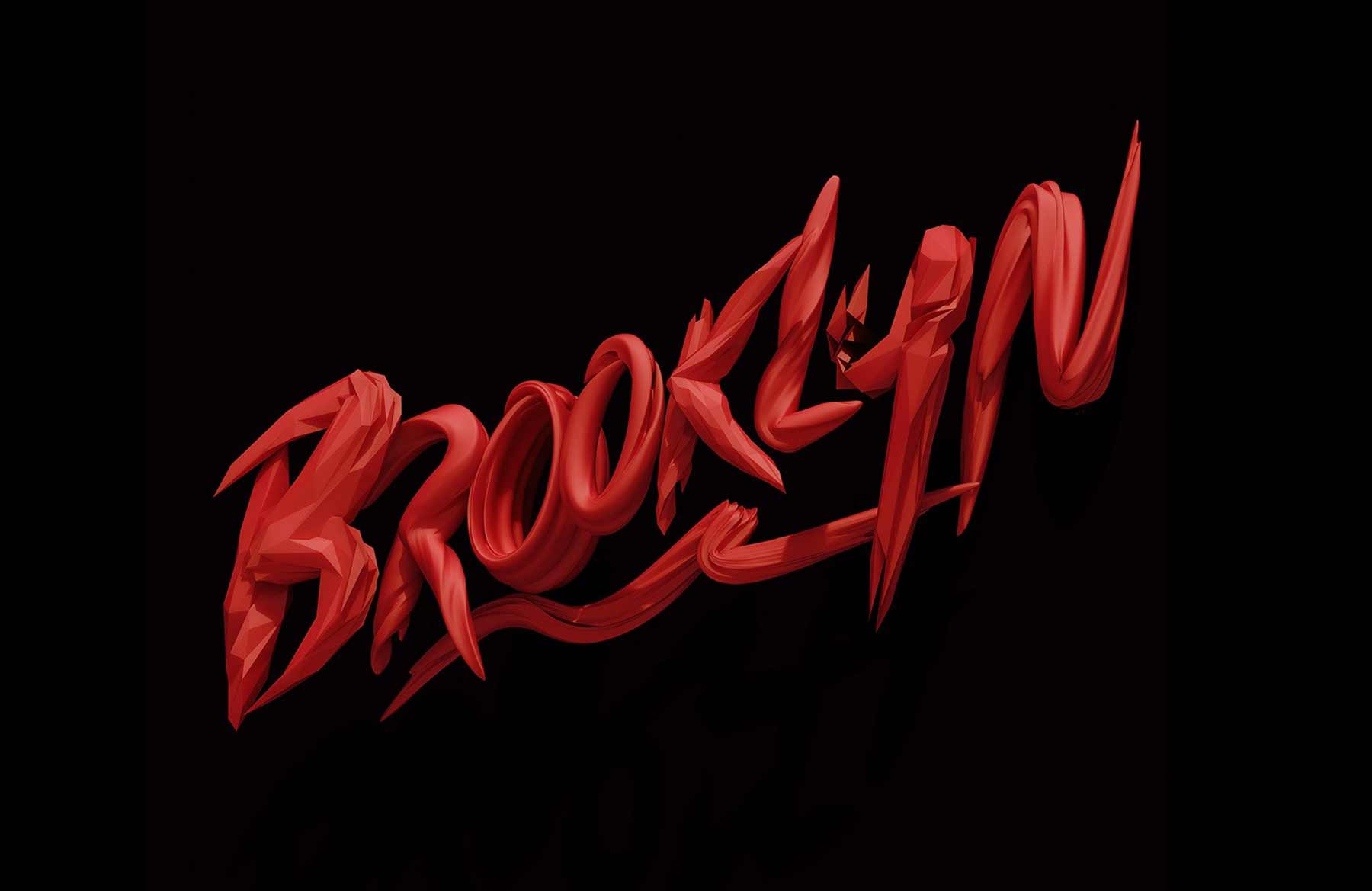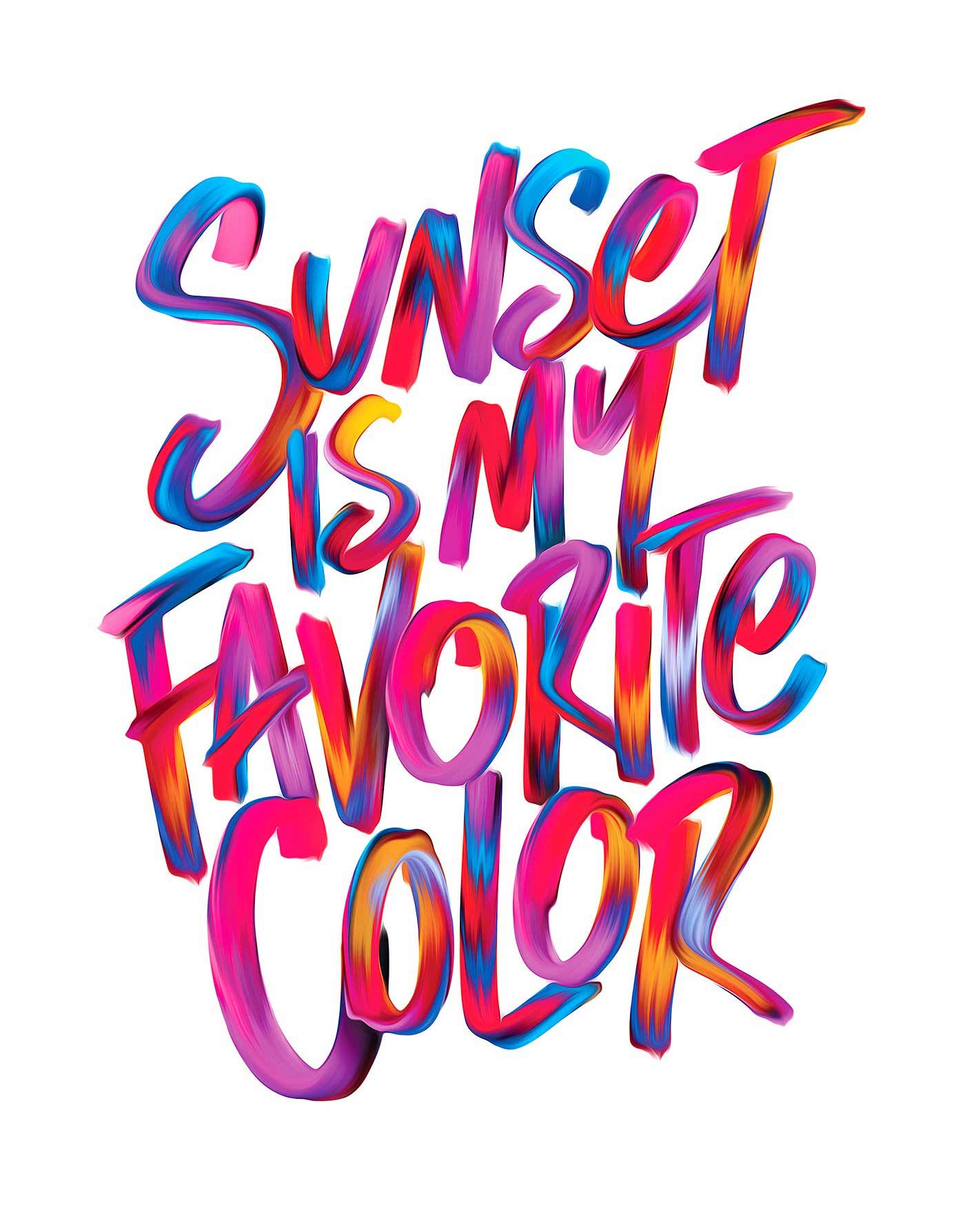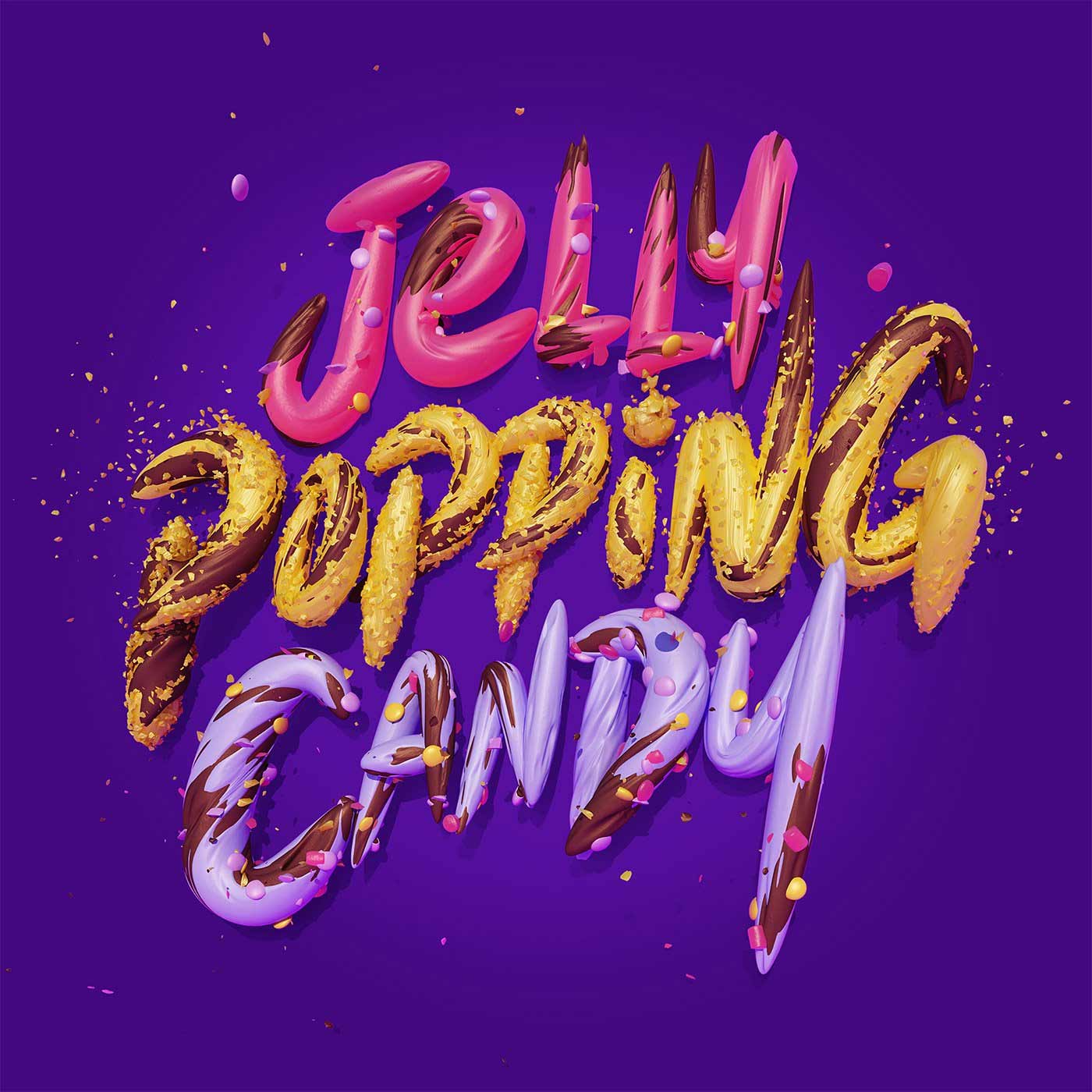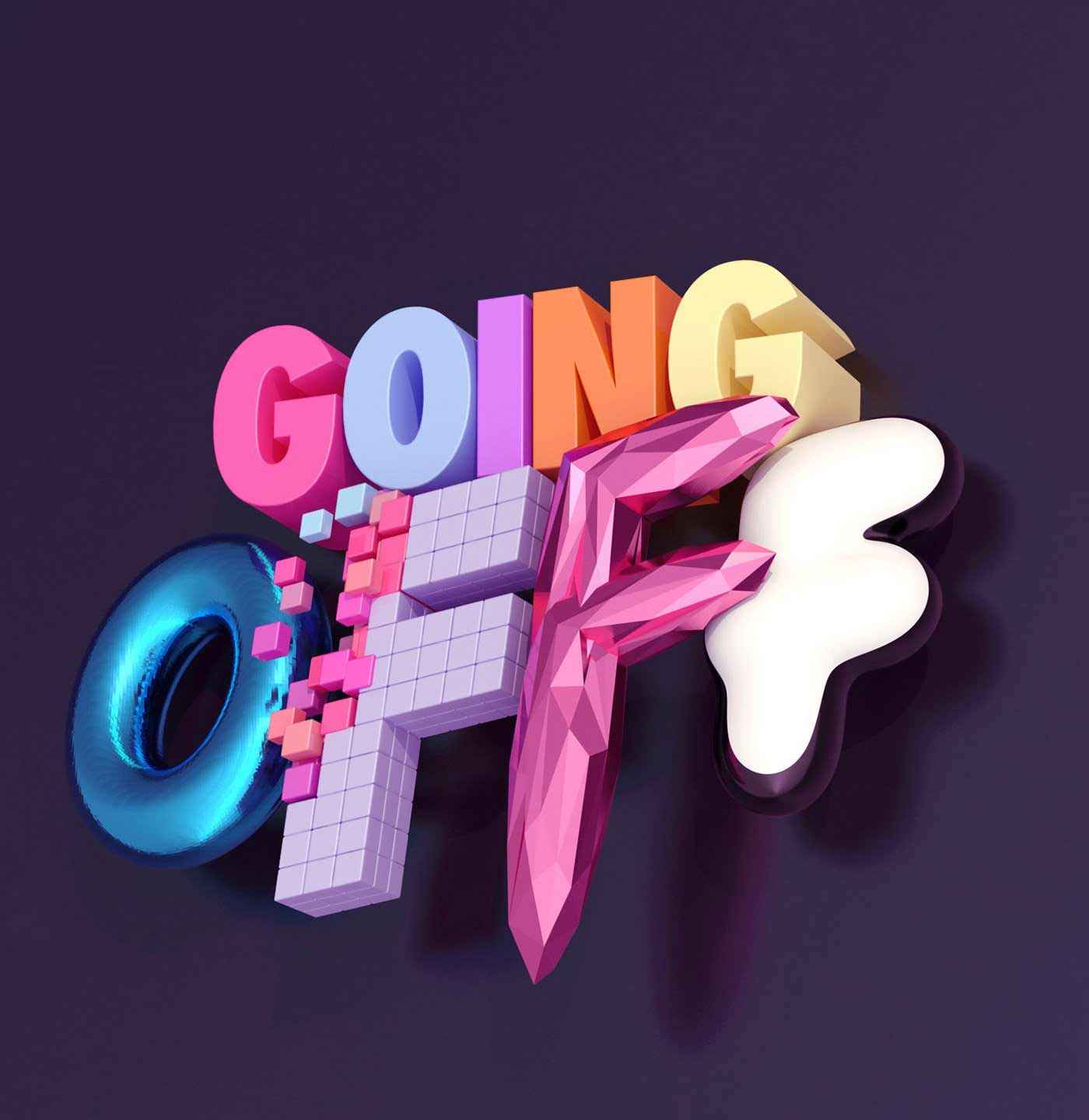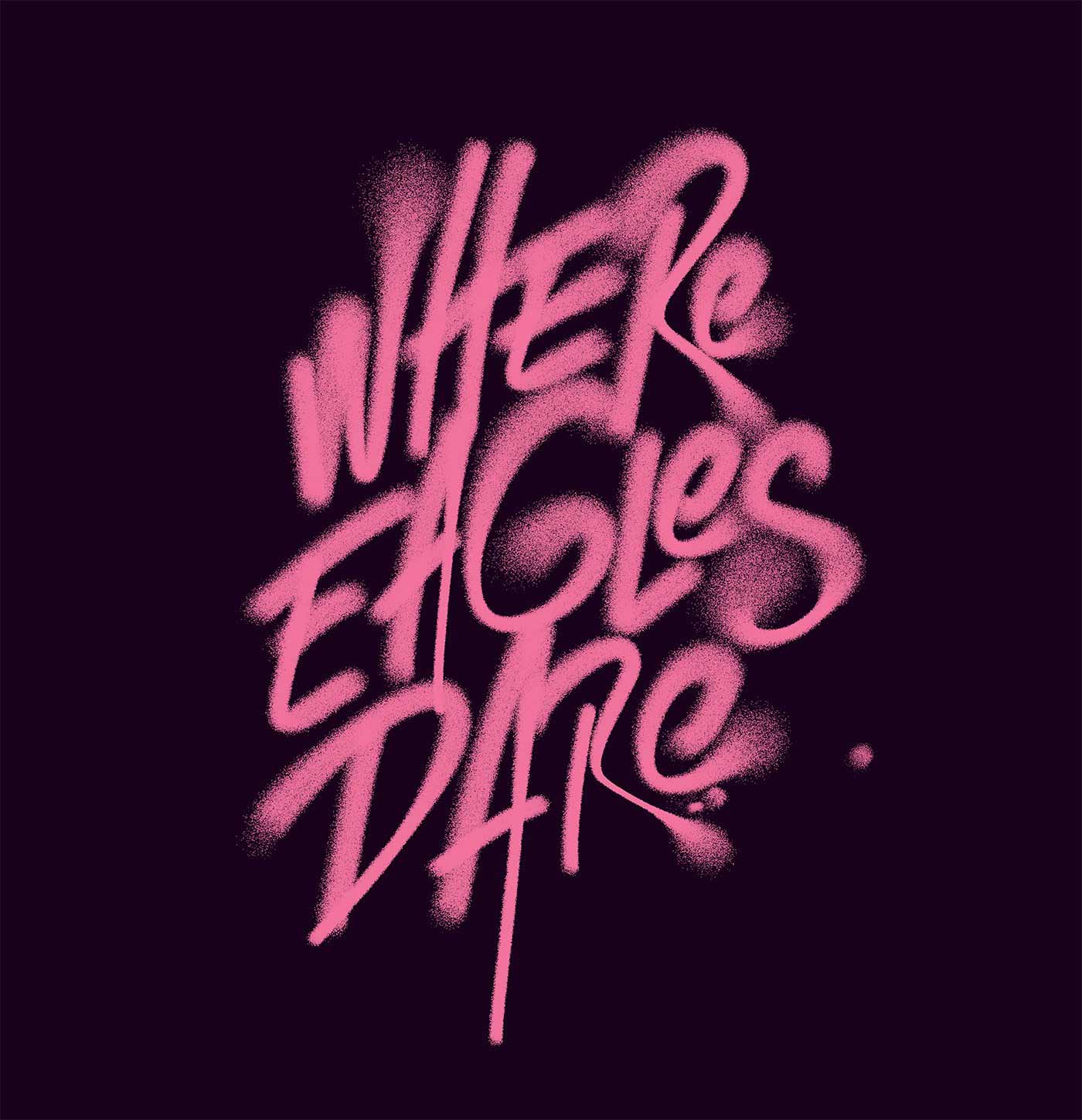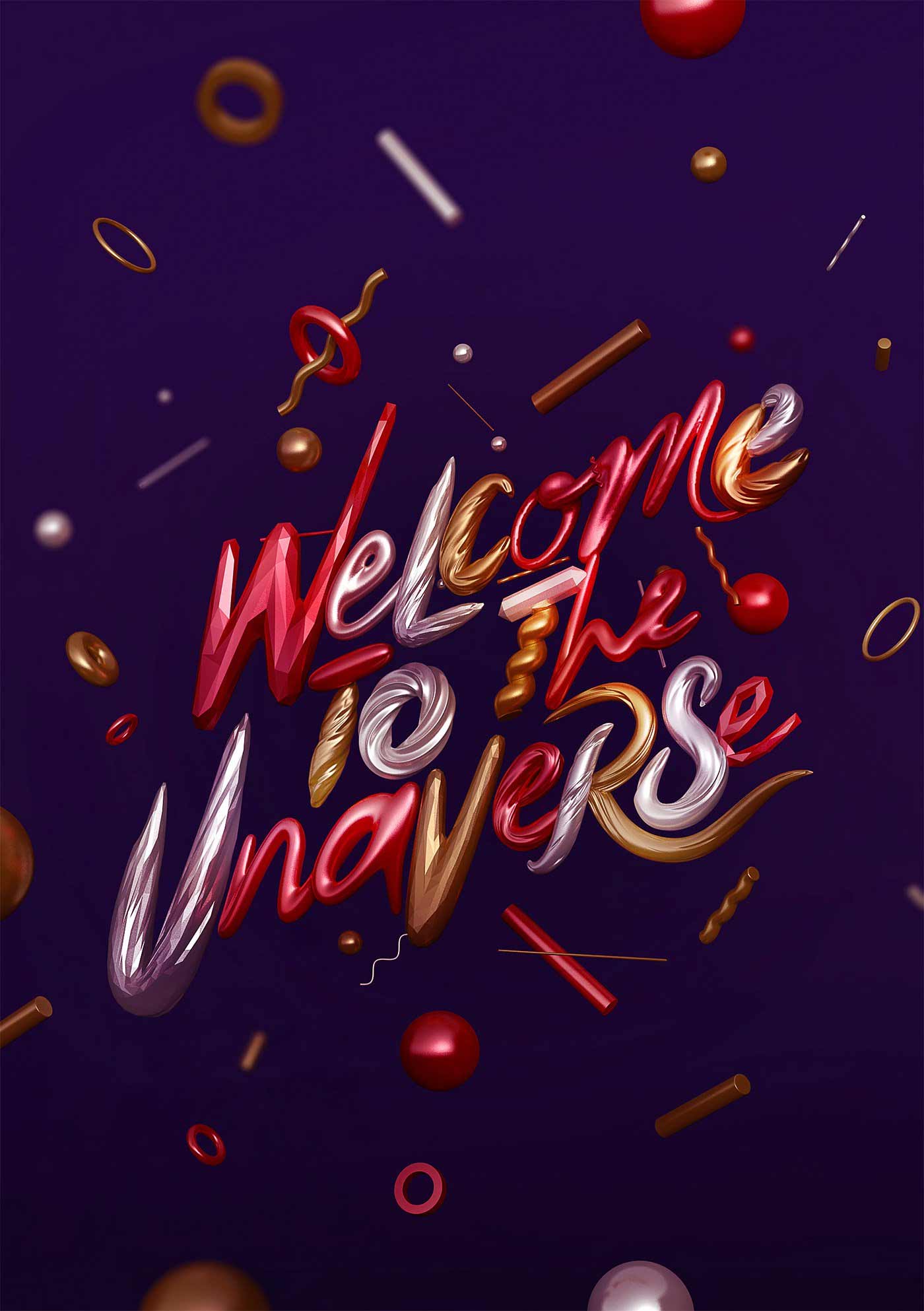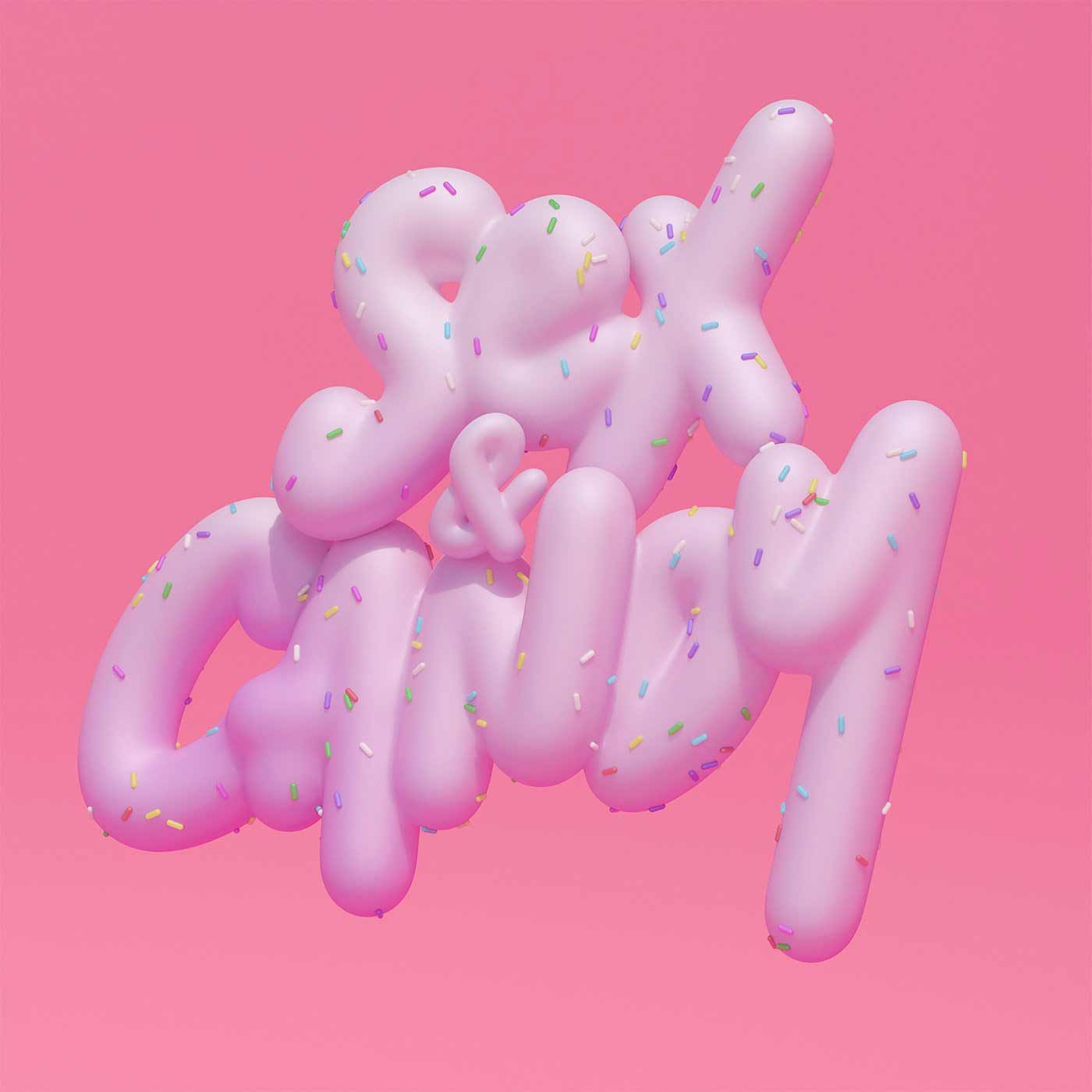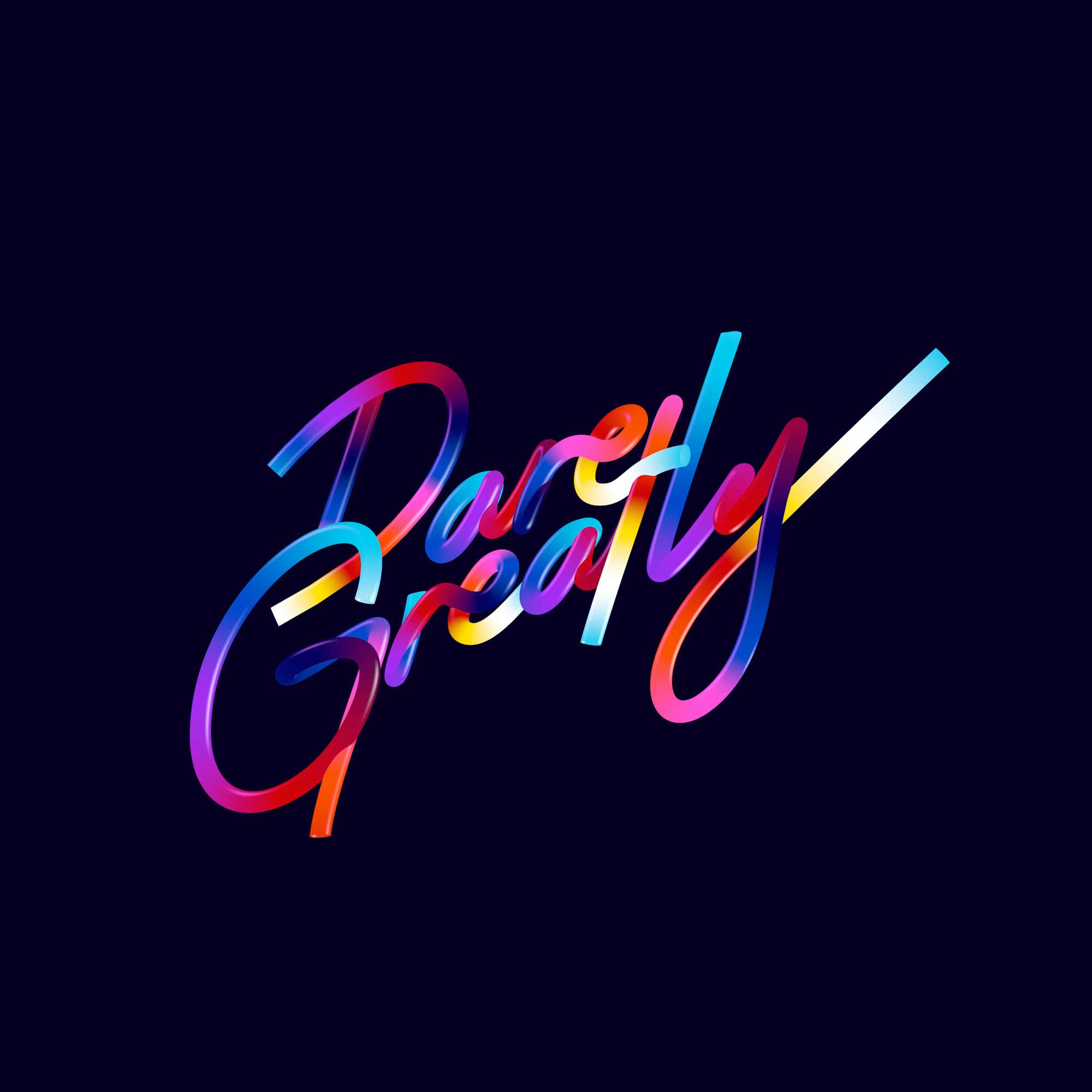
Abwechslungsreiche 3D-Arbeiten
Typografie: Luke Choice
Der aus Portland stammende Luke Choice aka Velvet Spectrum erstellt allerlei 3D-Grafiken für seine Kunden. Dabei spielt der Digital-Designer auch gerne mal mit Buchstaben herum und erstellt originelle wie abwechslungsreiche Schriftzüge, die mal total CGI-plastisch, mal analog-gemalt wirken. Hier eine kleine Auswahl für euch.
„Visual storytelling, with a strong foundation in dynamic color and composition, creates an eclectic portfolio that explores the surreal and unexpected. Working across multiple disciplines including 3D illustration, Typography and Animation for clients including…“ (Artist Statement)